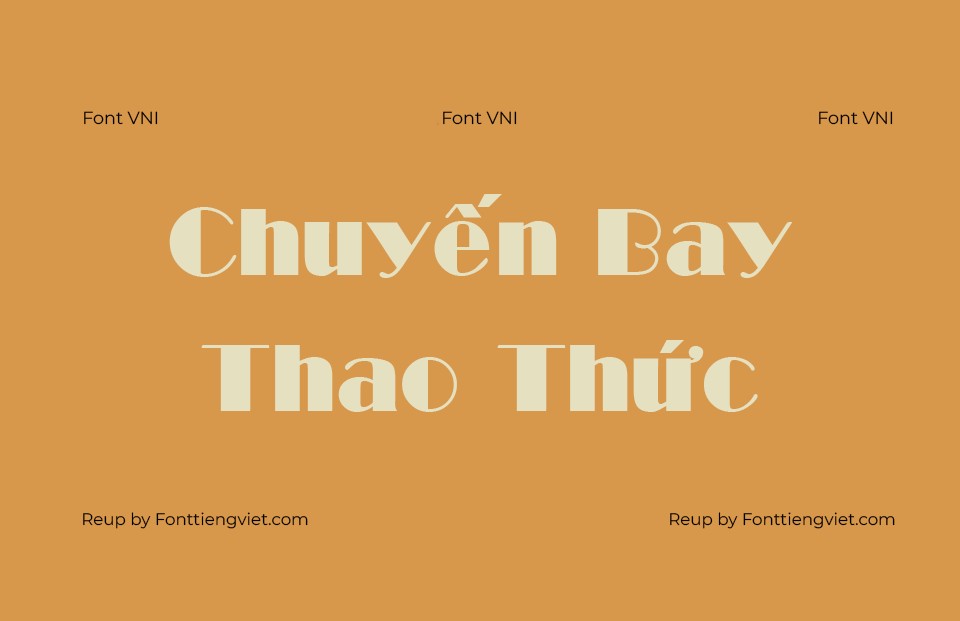
Font Việt hoá VNI Broad
Font Việt hoá VNI Broad – Bộ Font Chữ Nghệ Thuật Đỉnh Cao Cho Thiết Kế
Giới thiệu về bộ Font Việt hoá VNI Broad phổ biến
Trong thế giới thiết kế đồ họa tại Việt Nam, việc lựa chọn một Font Miễn Phí chất lượng luôn là ưu tiên hàng đầu của các bạn học sinh và giáo viên. Font Việt hoá VNI Broad nổi lên như một giải pháp hoàn hảo nhờ phong cách thiết kế đậm, chắc chắn và vô cùng mạnh mẽ. Đây là kiểu chữ lý tưởng để tạo điểm nhấn cho các tiêu đề báo tường, banner sự kiện trường học hay các bài thuyết trình chuyên nghiệp. Với bảng mã VNI truyền thống, bộ font này đã được tinh chỉnh kỹ lưỡng để hiển thị đầy đủ các dấu tiếng Việt mà không gặp lỗi hiển thị, giúp người dùng dễ dàng truyền tải thông điệp một cách trọn vẹn nhất.
Đặc điểm nổi bật của Font Việt hoá VNI Broad
Thiết kế dày bản và ấn tượng
Điểm khác biệt lớn nhất của Font Việt hoá VNI Broad chính là độ dày của các nét chữ. Điều này giúp văn bản trở nên nổi bật ngay cả khi nhìn từ khoảng cách xa. Các đường nét được bo góc tinh tế, mang lại cảm giác hiện đại nhưng vẫn giữ được sự gần gũi, phù hợp cho nhiều mục đích sáng tạo khác nhau từ in ấn đến trình chiếu kỹ thuật số.
Khả năng ứng dụng linh hoạt trong giáo dục
Không chỉ dùng trong quảng cáo, font chữ này còn xuất hiện rộng rãi trong các tài liệu giảng dạy. Giáo viên có thể dùng nó để trang trí trang bìa giáo án hoặc làm nổi bật các từ khóa quan trọng trên bảng tin. Sự ổn định của các ký tự giúp quá trình học tập và quan sát của học sinh trở nên trực quan và thú vị hơn bao giờ hết.